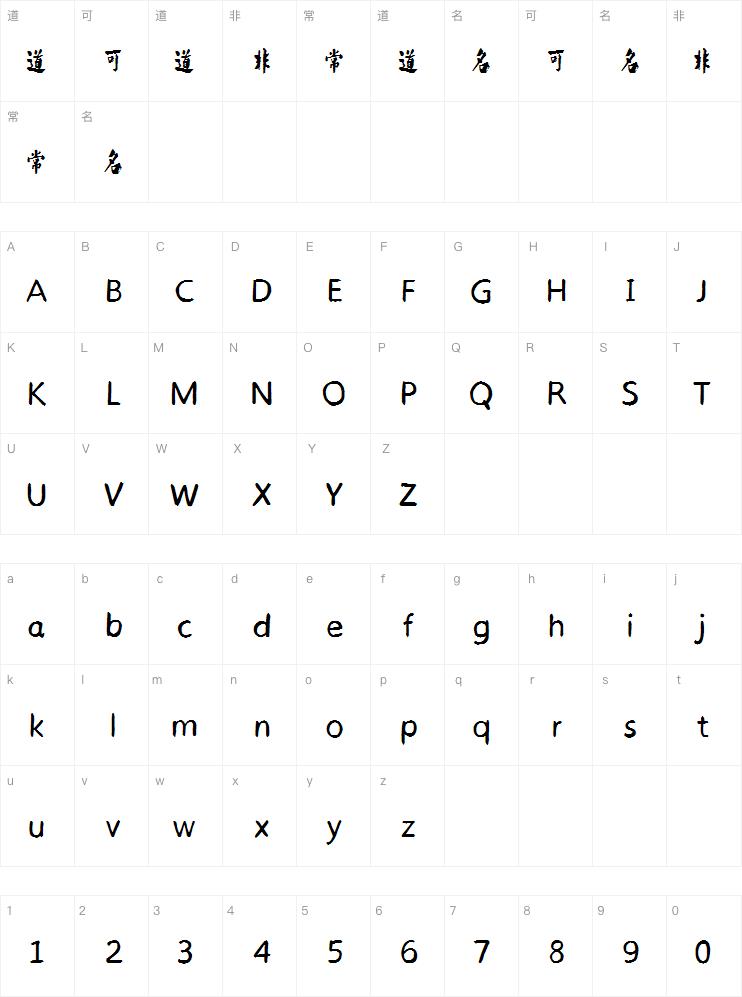
韩绍杰朱熹榜书是一款以宋代书法风格为基调的创意字体,融合了传统榜书的雄浑气韵与现代设计手法。其字形结构方正宽博,笔画粗犷有力,起笔收笔处可见隶书波磔的遗风,转折处又带有行书的流畅感,整体呈现出古朴厚重的历史沉淀。字体通过夸张的笔触对比与墨色枯润变化,模拟碑刻拓印的肌理效果,既保留了朱熹书法中"严正端方"的文人风骨,又注入了当代审美的简约张力。适用于文化主题海报、古籍封面、展览标题等场景,能传递出跨越时空的文脉传承与视觉冲击力。